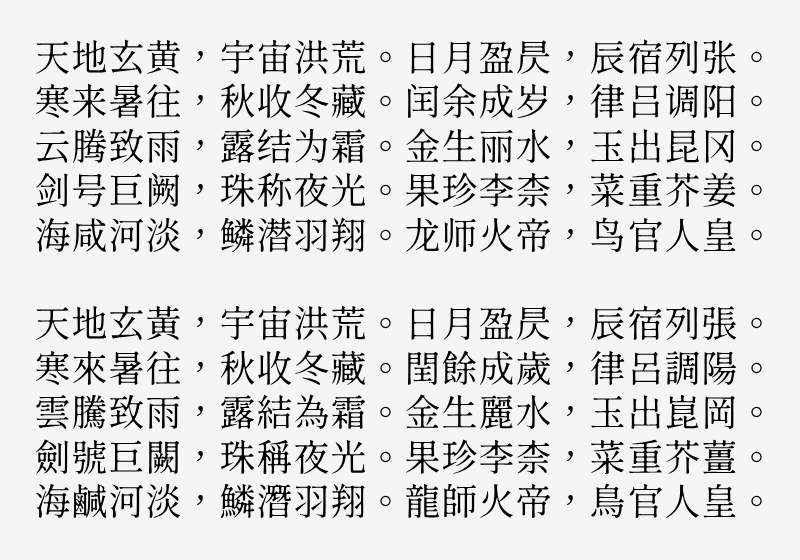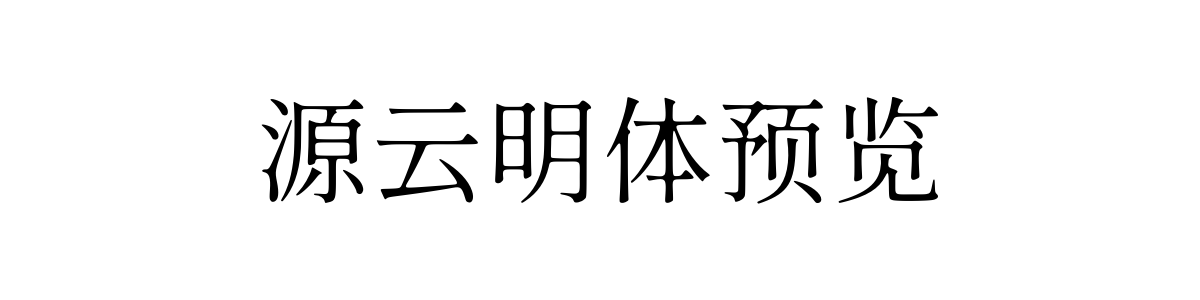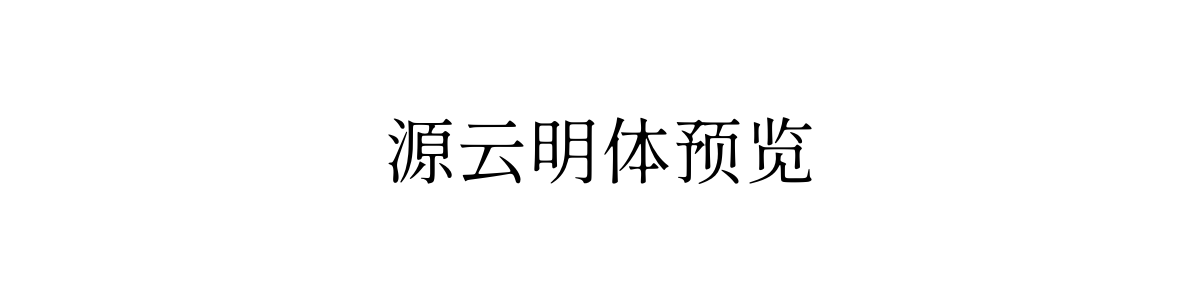
源云明体 2026年3月20日 上午12:07 • 中文字体 • 阅读 512 目录 字体预览字体风格字体下载 源云明体(GenWanMin)是一款以思源宋体为基础改造的开源中文字体。设计师在横笔起笔、竖笔起笔与收笔的位置加入了自然的粗细变化,同时在笔画交接处做了朦胧处理,让整体字形呈现出怀旧又感性的独特气质。 字体预览 源云明体 选择预设预览文本 选择预设文字 天地玄黄,宇宙洪荒。 雲騰致雨,露結為霜。 Hello, World 1234567890 !,、。!?:;“”‘’ A- A+ 自定义预览文本 选择字体字重 Light Regular Medium 字体风格 源云明体保留了宋体原本的端正结构,又通过细腻的笔画变化与朦胧处理,增添了柔和的人文感,风格温润耐看,自带怀旧氛围。 字体下载 源云明体 下载次数 43 字体类型 宋体 授权协议 OFL 授权类型 免费商用 刷新 OFL宋体日文简体繁体阅读字体 赞 (0) 0 0 生成海报 相关推荐 中文字体 余繁细柳体 余繁细柳体(YuFan XiLiu)是一款主打纤细感与清晰结构的中文标题字体,整体气质轻盈又不失骨力。设计上借鉴了仿宋的笔意特点,搭配大字面的字形结构,在保证视觉张力的前提下,把笔画做到极致细瘦,整体看上去如同柳枝一般,轻柔却又挺拔有力。 2026年3月22日 5310 中文字体 文津宋体 文津宋体(WenJin Mincho)是在思源宋体的基础上,结合 GlyphWiki 开源数据与修改版 Kage 引擎进行二次开发的大字符集宋体字库。它不只是简单的风格调整,而是一套完整的字符补全工程,能够完整覆盖 Unicode 规定的汉字以及 IVD 注册字形,并且统一采用中国大陆的字形标准。在目前免费商用的开源中文字体里,大字符集字库本身就不多,而像文津宋体这样严格遵循大陆标准、字符量又齐全的宋体更是少见,很好地填补了这一空白。 2026年3月17日 2390 中文字体 马善政毛笔楷书 马善政毛笔楷书(Ma Shanzheng)是由书法家马善政创作并授权发布的传统风格毛笔楷书字体,该字体是 Google Fonts 开源字体集合中的一员,由作者马善政本人授权钟齐字库整理并提交至该项目。 2026年1月29日 6050 中文字体 香萃潮汐宋 香萃潮汐宋是一款基于思源宋体改造而来的创意宋体,通过将笔画折角圆化并添加大量粘连处理,形成了柔和而富有张力的独特质感,兼具古典美感与现代清新气息。该字体以思源宋体为蓝本,进行了两项核心改造:一是将绝大多数笔画轮廓的折角改为圆角,二是刻意添加了笔画之间的粘连效果。这使得字体线条光滑流畅,曲线特征明显,整体呈现出清新明快的风格,同时因粘连处理而产生一种“藕断丝连”的朦胧感与蛛网般的视觉张力。 2026年3月9日 1431 中文字体 资源圆体 资源圆体(Source Han Rounded)是在思源黑体(Source Han Sans)基础上改造而成的开源圆体字库,它完整保留了原版优秀的字形结构和超大字库容量,只在细节上做了柔和化处理,把笔画末端和转角都改成顺滑的圆角,整体风格更温润,也更具现代感。 2026年3月30日 1.1K0 发表回复 请登录后评论...登录后才能评论 提交